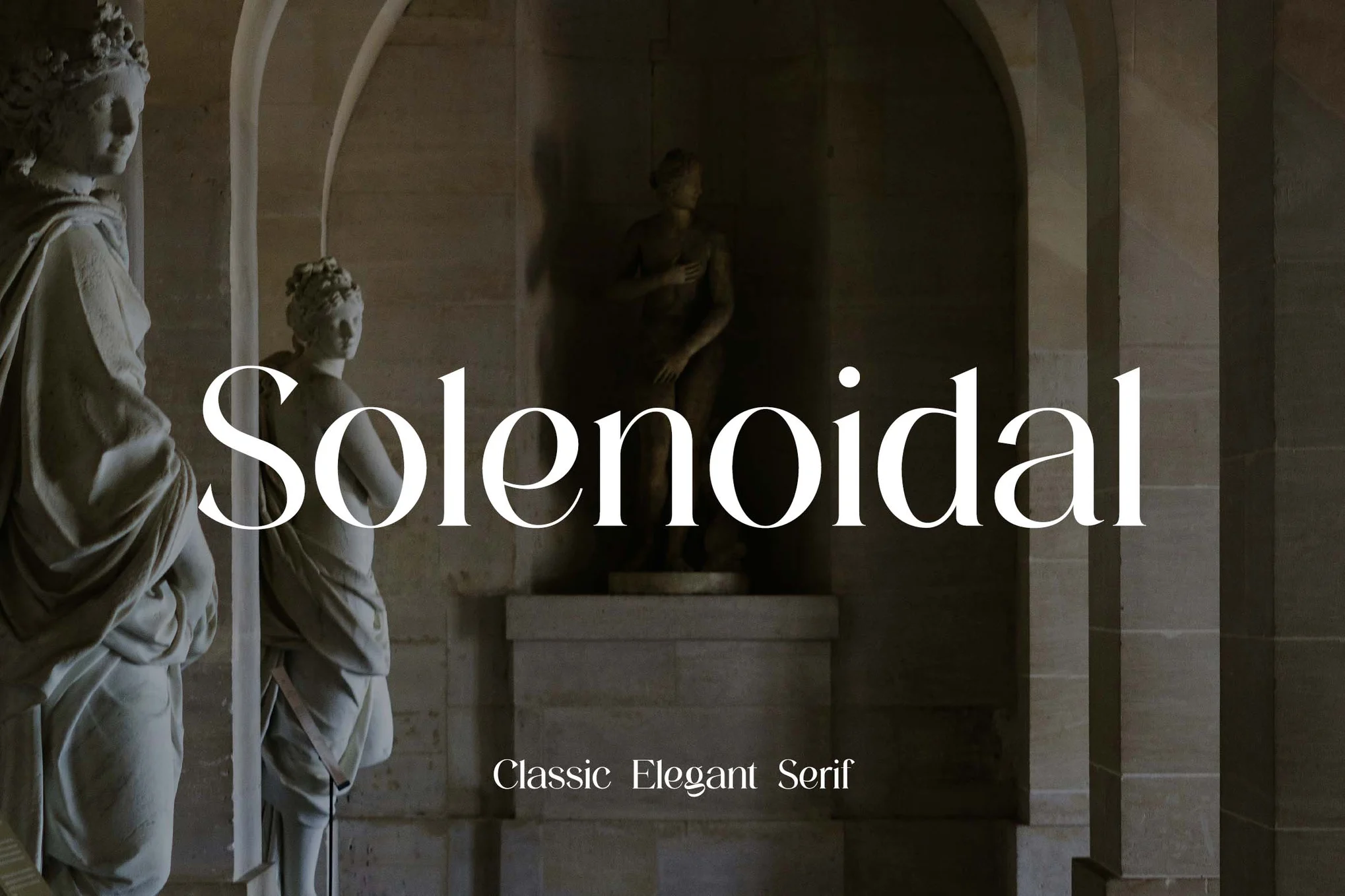
دانلود فونت Solenoidal Classic Elegant Serif Font
در معرفی محصول جدید خود، نام سلنوئیدال کلاسیک Elegant Serif Font است. فونت کلاسیک سریف که ظاهری زیبا، شیک و مدرن دارد. این فونت ایده آل برای پروژه های مختلف مانند امضا، لوازم التحریر، لوگو، عروسی، نقل قول تایپوگرافی، جلد مجلات یا کتاب، هدر وب سایت، لباس، برندسازی، طراحی بسته بندی و غیره است. همچنین، برندسازی مرتبط با مد یا طراحی سرمقاله، ویژگیهای مردانه و زنانه را نشان میدهد.